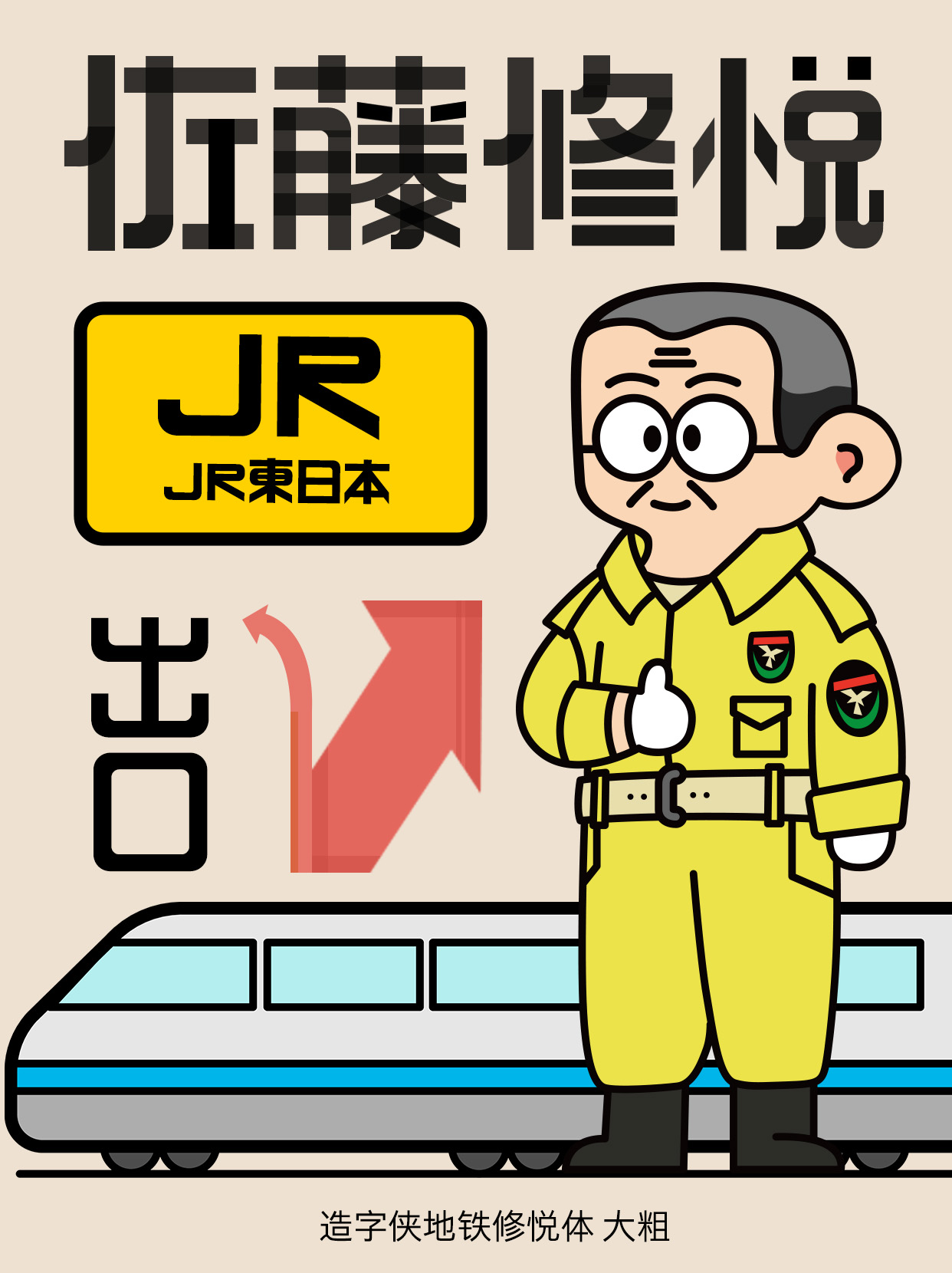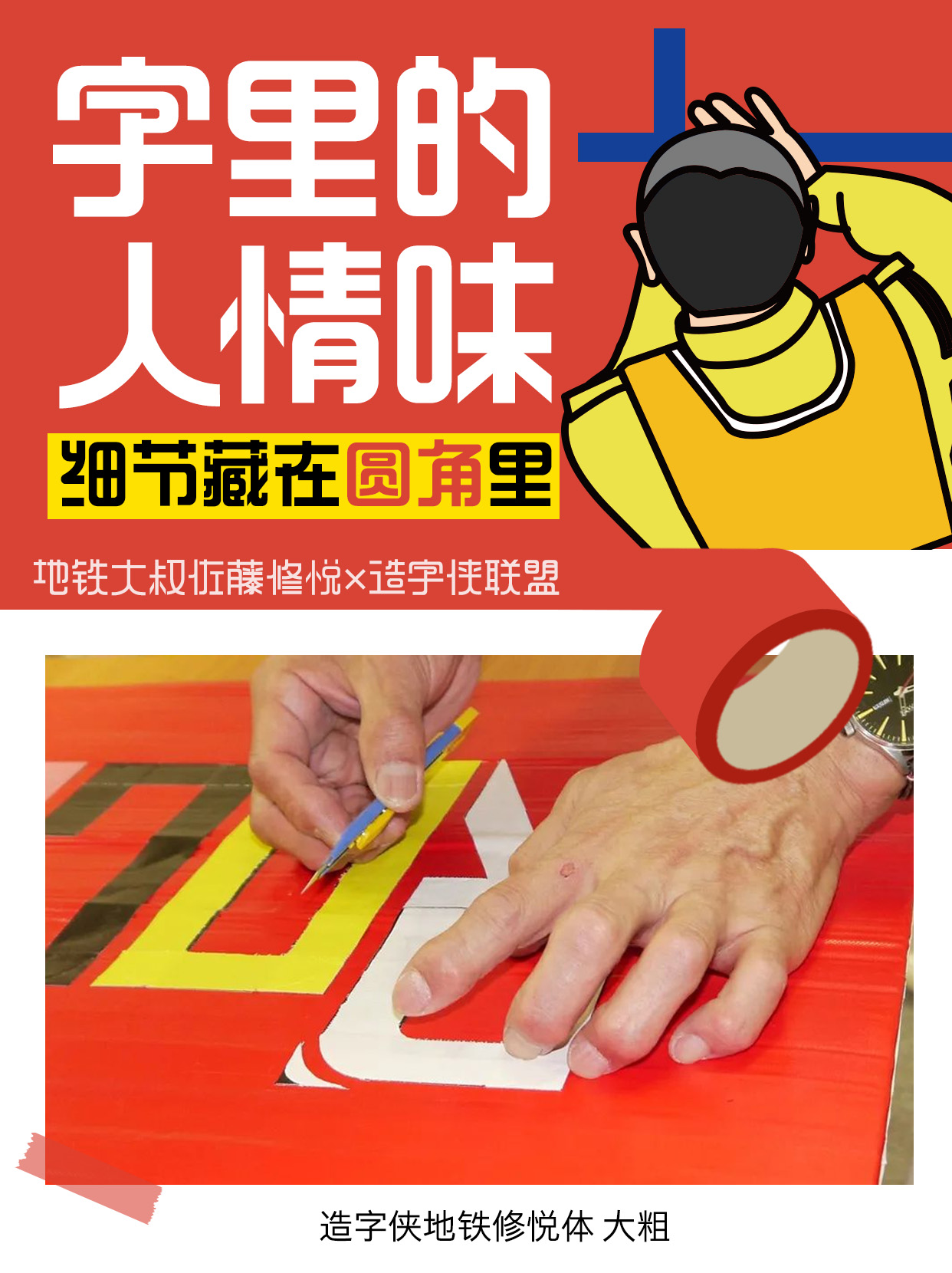
造字侠地铁修悦体 大粗
PlayFont-SyuetsuGB Bold
造字侠地铁修悦体是一款以胶带为灵感创作的系列化创意黑体家族,它来源于地下铁工作员佐藤修悦的真切热心,为了方便地铁乘客快速寻路,他用胶带在墙上拼贴成的醒目的指路文字,增加了乘客的通行效率。
字体的造型方正,笔画切口平直,造型充满胶带制作带来的几何风格,结构上可以保留人工拼贴的手工不规律性,造成了多变的重心和留白,风格与视觉的强烈冲击使字体排版时充满趣味与个性,让人的注意力一眼就被吸引过去。该字体适用于海报宣传、广告标题、文创周边等。